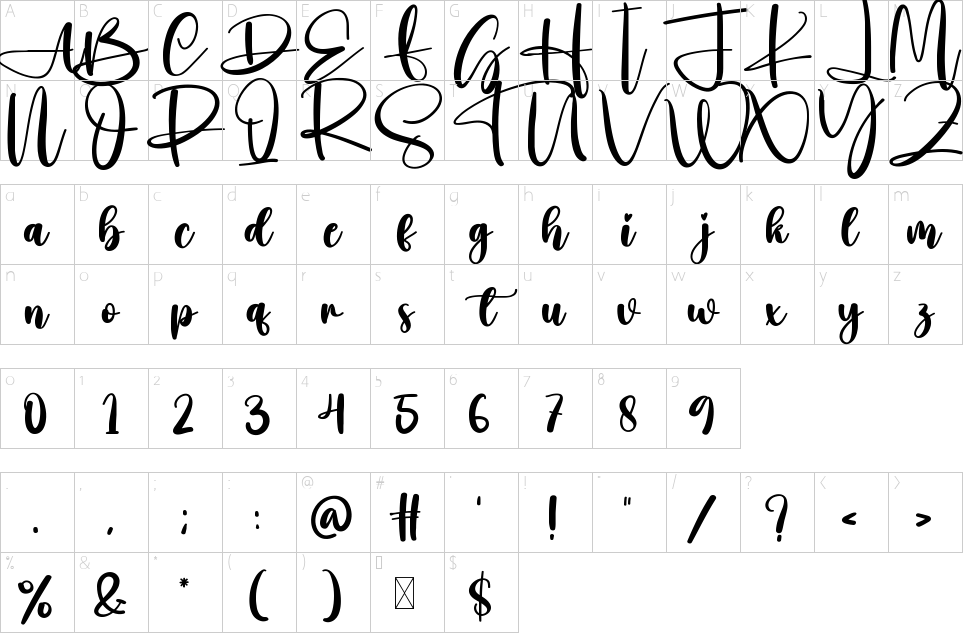
Descubra a sofistica e a facilidade que a fonte “Already” oferece para seu próximo projeto. Desenvolvida pelo designer scratchones, a “Already” é uma fonte que encaixa-se perfeitamente em qualquer projeto gráfico, seja ele para a web, em impressão ou em designs digitais. Com uma aparência elegante e uma leitura fluida, a “Already” é uma escolha perfeita para quem procura uma fonte de alta qualidade sem precisar pagar nada. Com seu design moderno e versátil, a “Already” tem sido uma escolha popular entre designers e profissionais de gráficos, e já foi baixada mais de 500 vezes. Não deixe de experimentar a “Already” e veja por você mesmo a qualificação de sua fonte favorita. Download já e comprove!